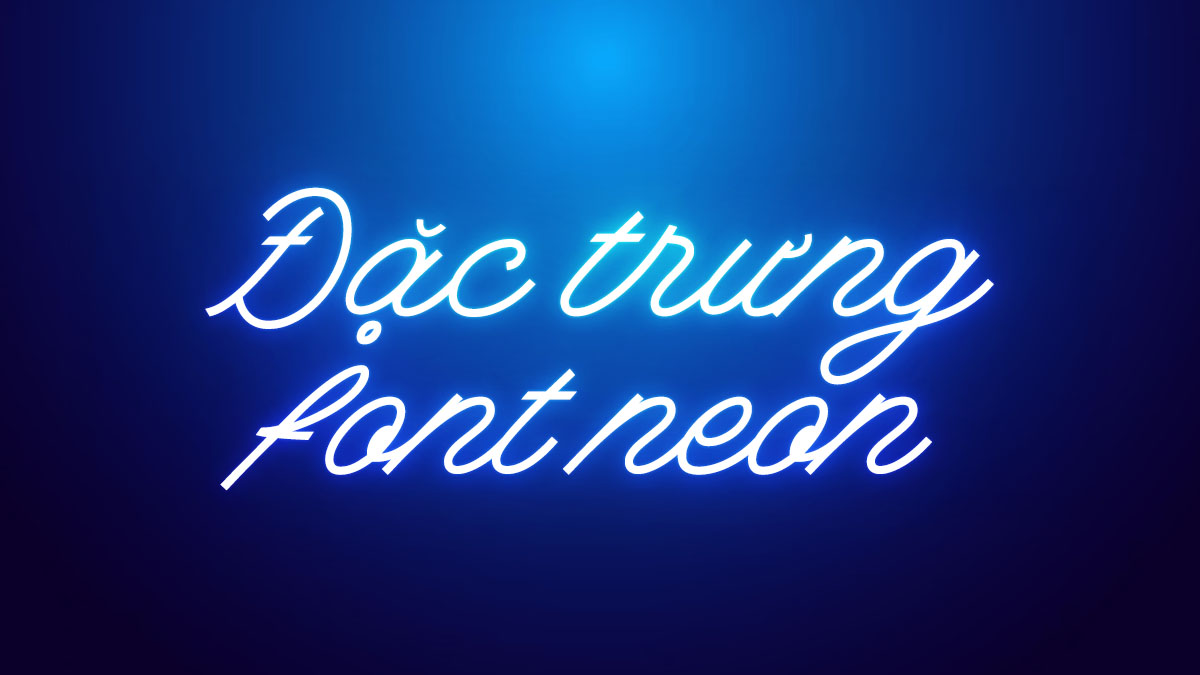
Font chữ led neon là gì và sức hút của phông chữ đèn neon trong đồ họa?
Font chữ led neon là nhóm phông nghệ thuật mô phỏng hình dáng các ống đèn neon uốn lượn, mang đặc trưng là các nét chữ thanh mảnh, bo tròn và có khoảng hở uốn khúc tự nhiên. Điểm nhấn của font chữ đèn neon nằm ở khả năng giả lập ánh sáng rực rỡ trên nền tối, khơi gợi cảm giác hoài cổ của những năm 80 kết hợp cùng phong cách Cyberpunk hiện đại. Đây là lựa chọn phù hợp cho thiết kế logo quán bar, bao bì sản phẩm công nghệ hoặc các ấn phẩm sự kiện ban đêm.
Sức hút của dòng phông này còn nằm ở cấu trúc đường path liên tục, giúp việc truyền tải thông điệp trở nên linh hoạt và giàu cảm xúc. Các mẫu font chữ làm led neon giúp xóa bỏ sự đơn điệu của các bộ nhận diện thông thường, mang lại hơi thở của sự năng động và đổi mới.
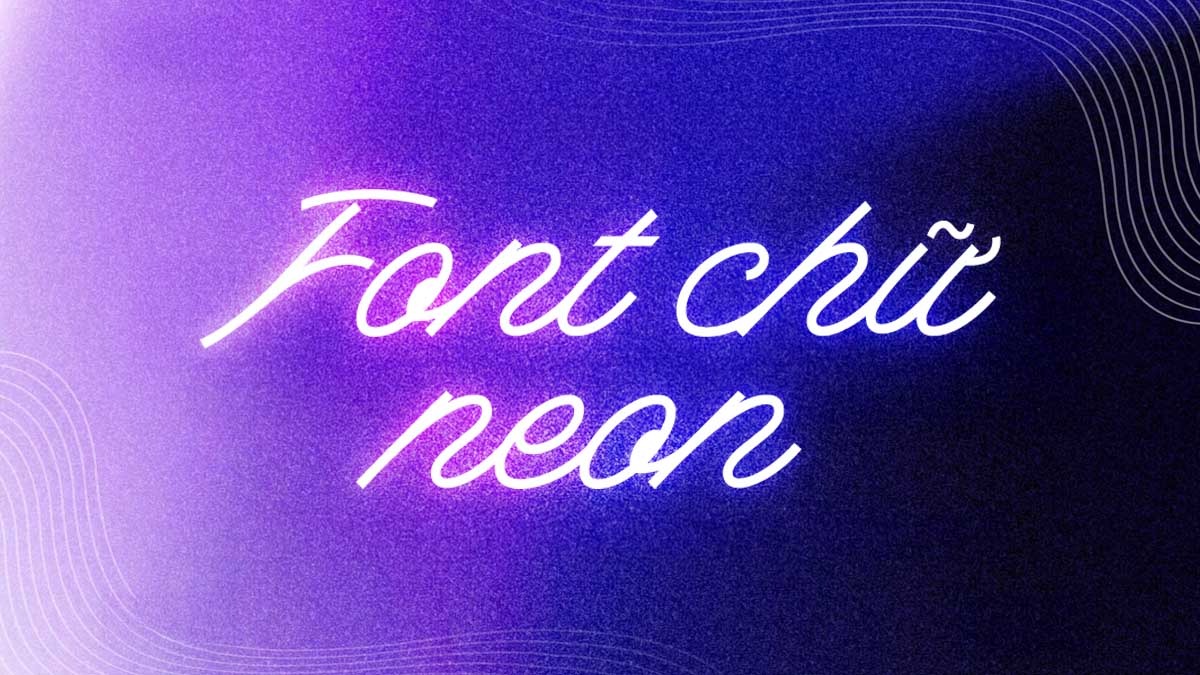
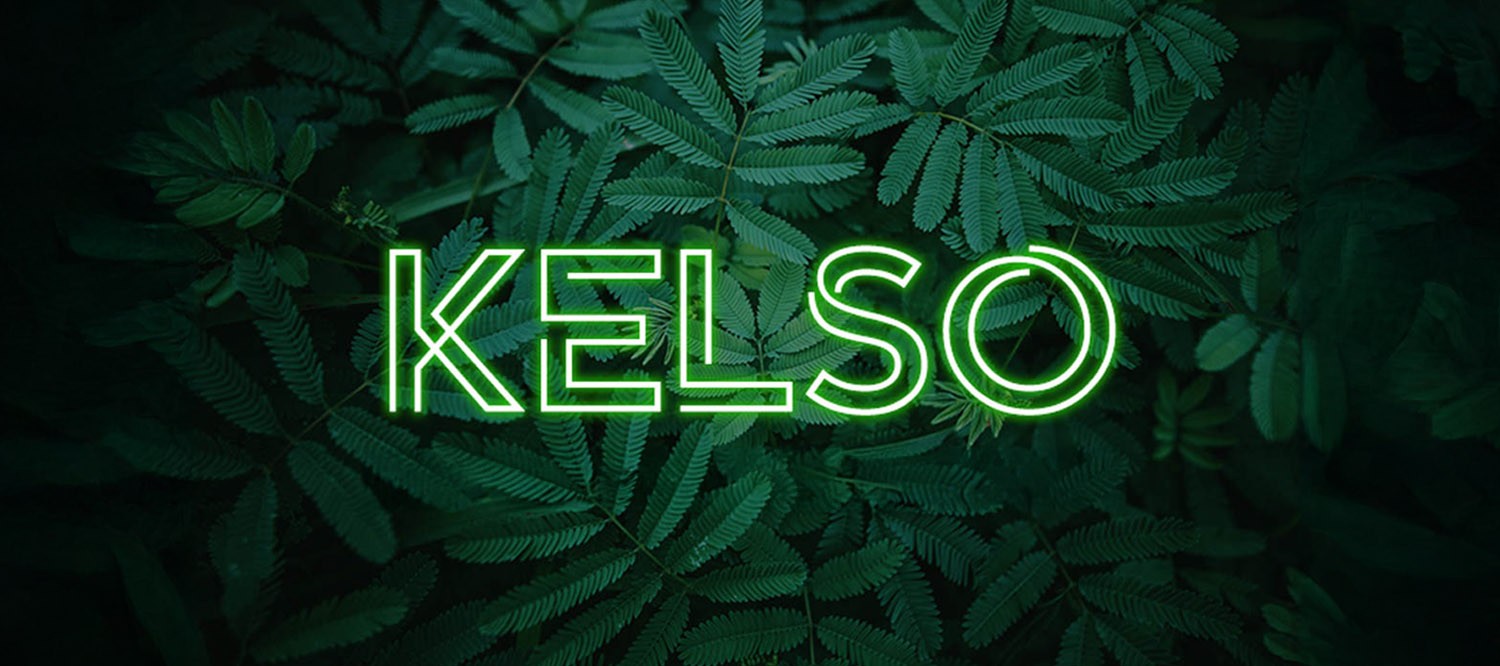
05 Ứng dụng thực tế của font chữ đèn led neon trong truyền thông thương hiệu
Vẻ đẹp rực rỡ và phong cách hiện đại của phông chữ ánh sáng nâng tầm giá trị cho nhiều ấn phẩm truyền thông của đơn vị:
- Thiết kế biển hiệu và bảng quảng cáo trang trí: Font chữ làm đèn led neon là thành phần cốt lõi để tạo nên các bảng tên cửa hàng hay slogan tại quầy thu ngân. Độ sắc sảo của phông chữ giúp thợ gia công dễ dàng uốn dây led theo đúng hình dáng bản vẽ, đảm bảo độ thẩm mỹ cao cho không gian kinh doanh.
- Sản xuất bao bì hộp quà tặng công nghệ: Sử dụng kiểu chữ neon cho tiêu đề trên các dòng vỏ hộp giấy Ivory đựng tai nghe, sạc dự phòng. Những đường nét uốn lượn mang hơi hướng kỹ thuật số tạo cảm giác sản phẩm hiện đại, dễ dàng ghi điểm với khách hàng trẻ tuổi.
- Gia công in UV trên các hiện vật văn phòng: Logo lồng ghép cùng font chữ led neon được in trên bình giữ nhiệt kim loại hoặc sổ tay bìa cứng. Công nghệ in tại In Viva giúp các hiệu ứng màu neon hiển thị sắc sảo, bền màu theo thời gian sử dụng thường ngày.
- Trang trí voucher và phiếu giảm giá điện tử: Một dòng chữ mang phong cách ánh sáng trên thẻ thành viên giúp tạo điểm nhấn độc đáo, mang lại cảm giác mới mẻ và cuốn hút cho người sở hữu các tấm thẻ này trong các chiến dịch marketing.
- Đồng bộ bộ nhận diện sự kiện âm nhạc: Sử dụng kiểu chữ này cho các tiêu đề trên backdrop sân khấu hay banner chào mừng giúp không gian buổi lễ toát lên sự năng động, trẻ trung và bắt kịp xu hướng thời đại.
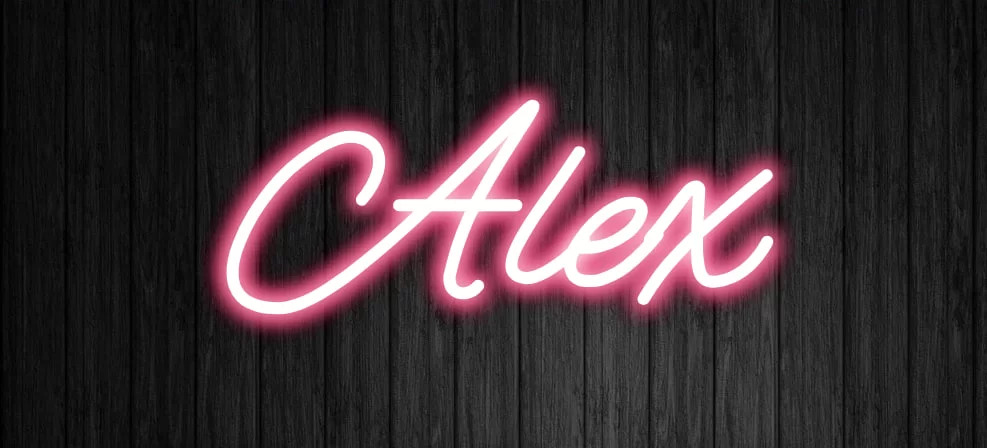
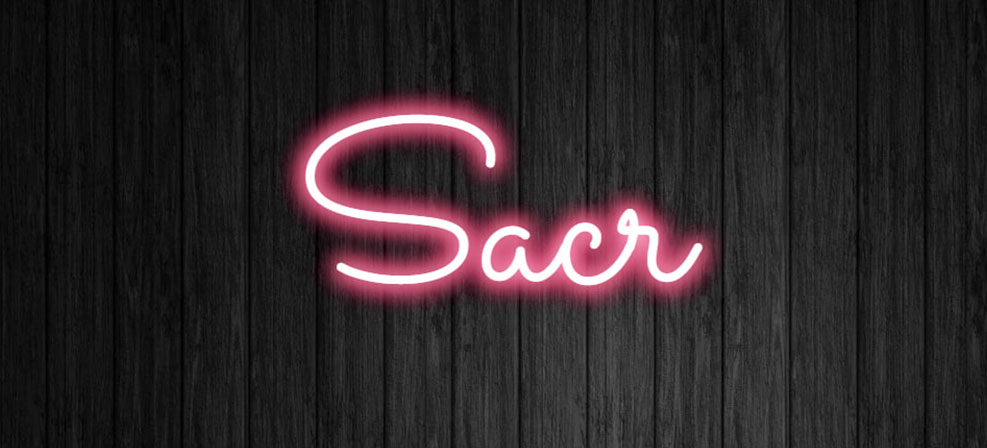
04 Lưu ý kỹ thuật khi xử lý font chữ led neon phục vụ in ấn
Để hệ thống ký tự ánh sáng hiển thị sống động và bền màu trên các thành phẩm thực tế như túi giấy cao cấp hay hiện vật tri ân đối tác, designer cần chú trọng:
- Kiểm soát mật độ chi tiết đường ống: font chữ led neon thường mô phỏng các ống thủy tinh rỗng. Khi in ấn kích thước nhỏ trên tem nhãn, designer nên tăng nhẹ độ dày nét để mực bám ổn định, tránh tình trạng chữ bị mờ nhạt hoặc đứt đoạn do mực không thoát đều.
- Tối ưu đường Path cho gia công bế nổi: Khâu này đặc biệt cần thiết khi sản xuất nắp hộp cứng dập nổi logo doanh nghiệp theo phong cách neon. Kỹ thuật viên cần làm mượt từng điểm neo bo tròn trong file vector giúp khuôn bế thực hiện chính xác, tạo hiệu ứng nổi khối rạng rỡ cho các chi tiết uốn lượn.
- Thiết lập hệ màu CMYK cho hiệu ứng phát sáng: Màu sắc neon trên màn hình (RGB) thường rực rỡ hơn thực tế. Designer cần hiệu chỉnh hệ màu CMYK chuẩn in ấn tại xưởng và yêu cầu xưởng in lót mực trắng bên dưới nếu in trên bề mặt tối để bảo toàn độ bắt mắt của hình ảnh.
- Xử lý độ trong suốt của bóng đổ (Glow effect): Để phông chữ trông như đang tỏa sáng thật, bạn cần xử lý kỹ dải màu chuyển (Gradient). Hãy thảo luận với xưởng về kỹ thuật in UV định hình để tạo lớp màng bóng lên nét chữ, giúp giả lập hiệu ứng ánh sáng chân thực nhất trên bề mặt giấy Ivory.